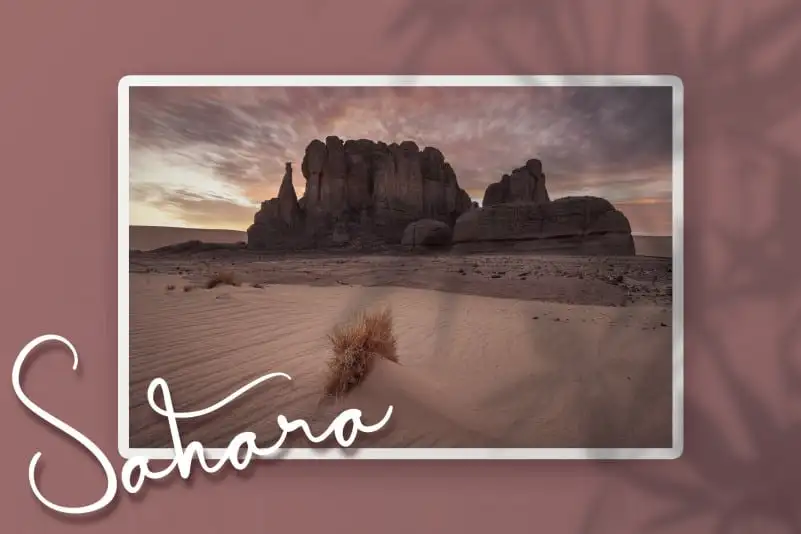
Algeria Script Font
A Algeria Script Font é uma deliciosa aquarela do tipo tipográfico, com sua forma cívilizada e detalhada que brinca ao redor das palavras, oferecendo um tom suave e elegante para qualquer projeto. Este font atende perfeitamente como o companheiro ideal de seu acervo de fontes, iluminando seus trabalhos com uma delicadeza única que torna todas as criações mais atraentes e sofisticadas. Em um mundo onde cada detalhe conta, esta font é certamente algo a ser adquirido para qualquer designer que busca trazer vida e complexidade ao seu trabalho de design.